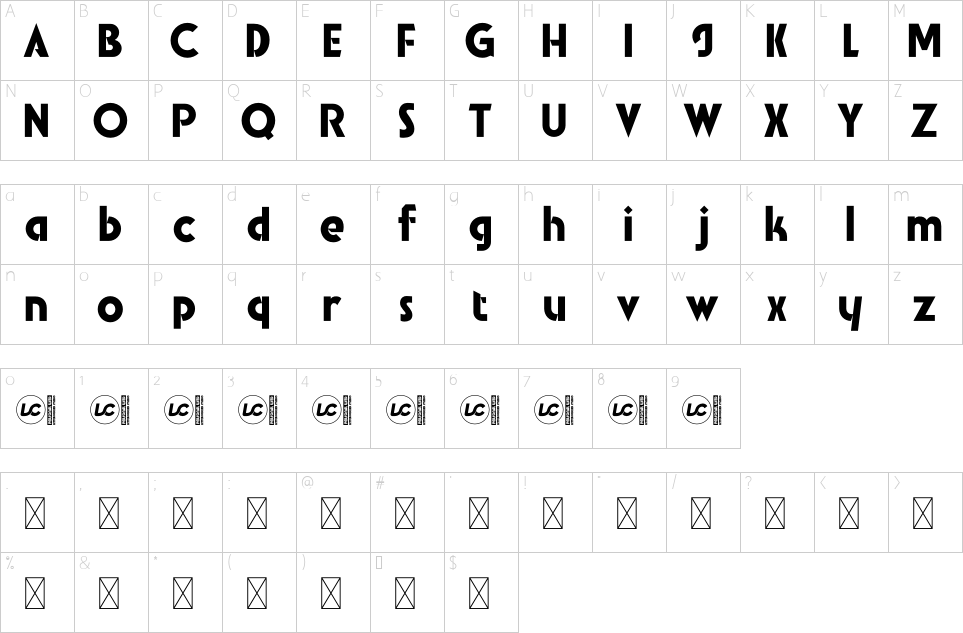
Descubra o encanto da Aprl Font, uma fonte digital totalmente gratuita disponível tanto para Windows quanto para Mac. Desenvolvida por Lettercorner Studio, esta elegante fonte oferece um toque moderno e sofisticado a qualquer projeto gráfico. Com apenas um clique, você pode incorporar a Aprl Font em seus documentos, gráficos ou qualquer projeto que precise de uma fonte fluida e de fácil leitura. Com uma baixa embaçagem e um design minimalista, a Aprl é uma escolha ideal para designers que buscam uma fonte moderna e funcional. Esta fonte já foi baixada mais de 1.315 vezes, evidenciando seu valor e qualidade. Experimente agora a Aprl Font e deixe seu trabalho de design mais profissional e elegante.